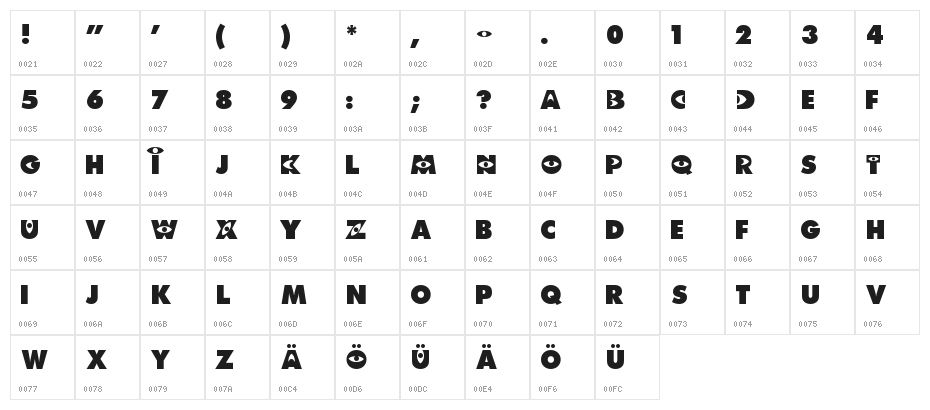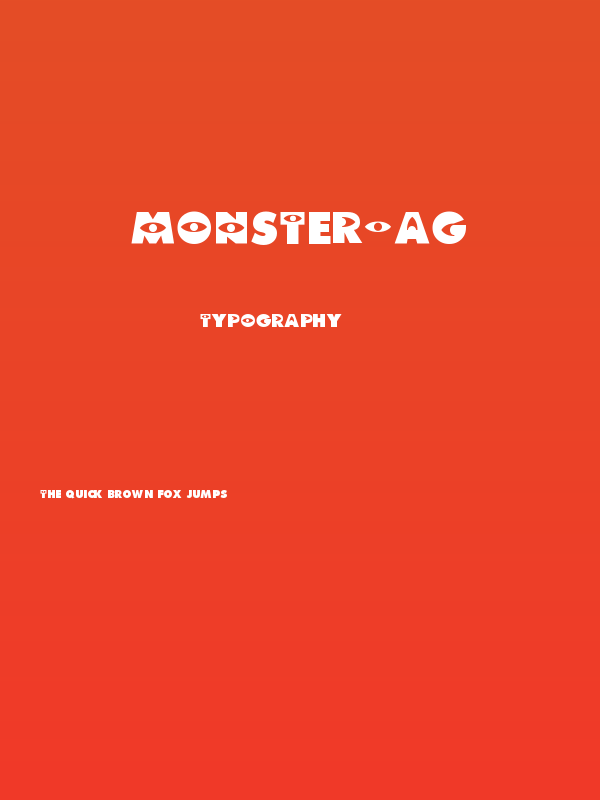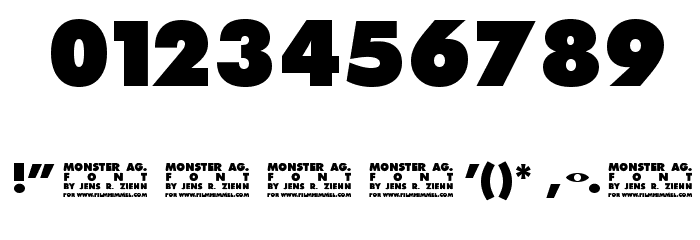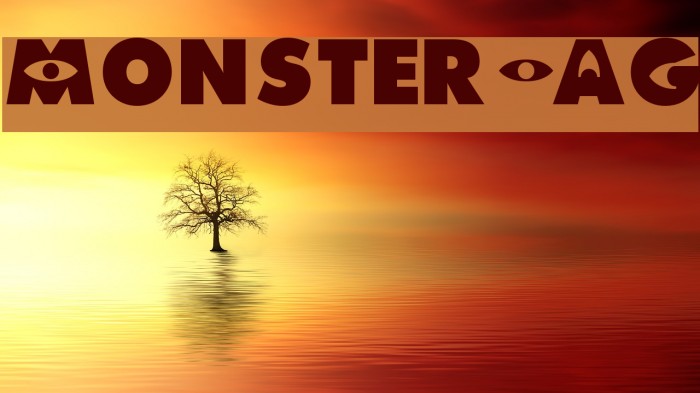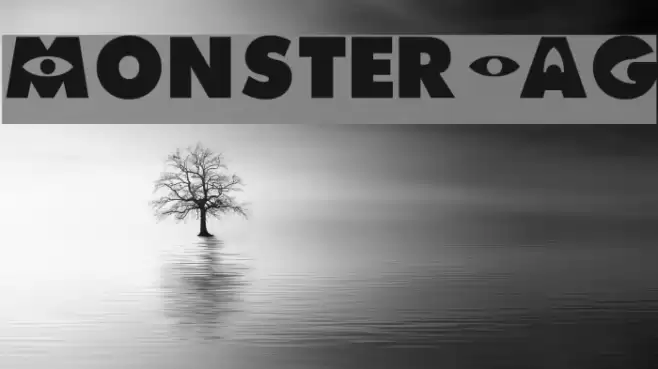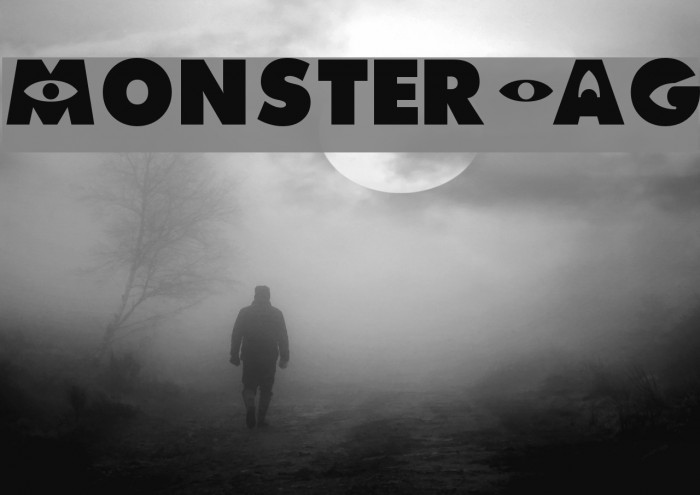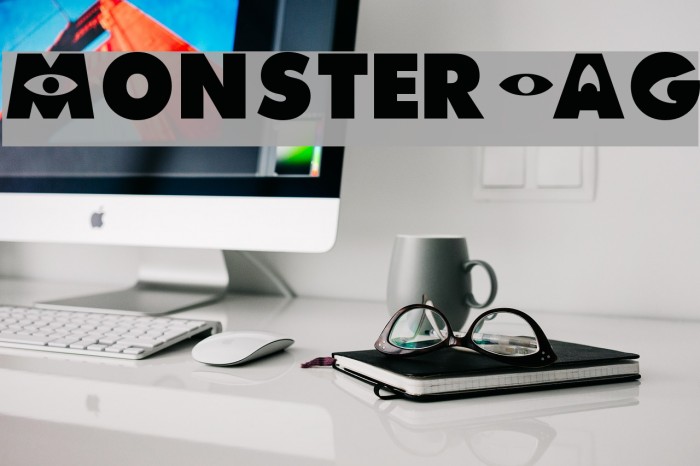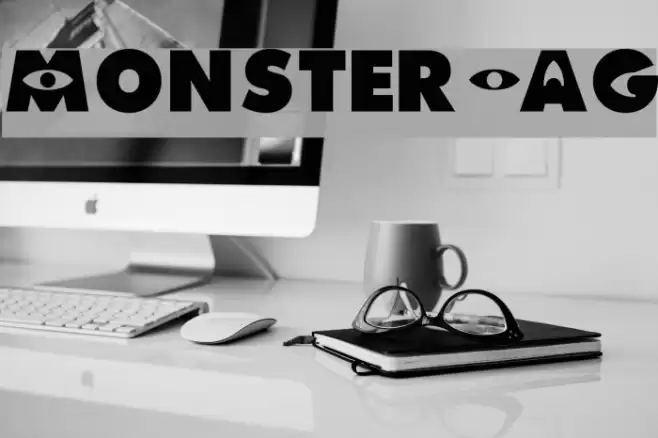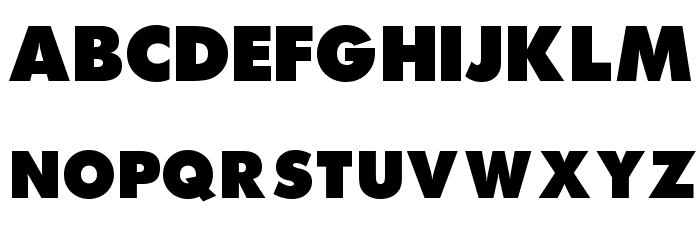
Monster-AG Font
| Stil general | Playful, Quirky, Fun |
| Proiecte propuse | Ideal for children's book covers, playful branding, themed event posters, and creative advertising campaigns. |